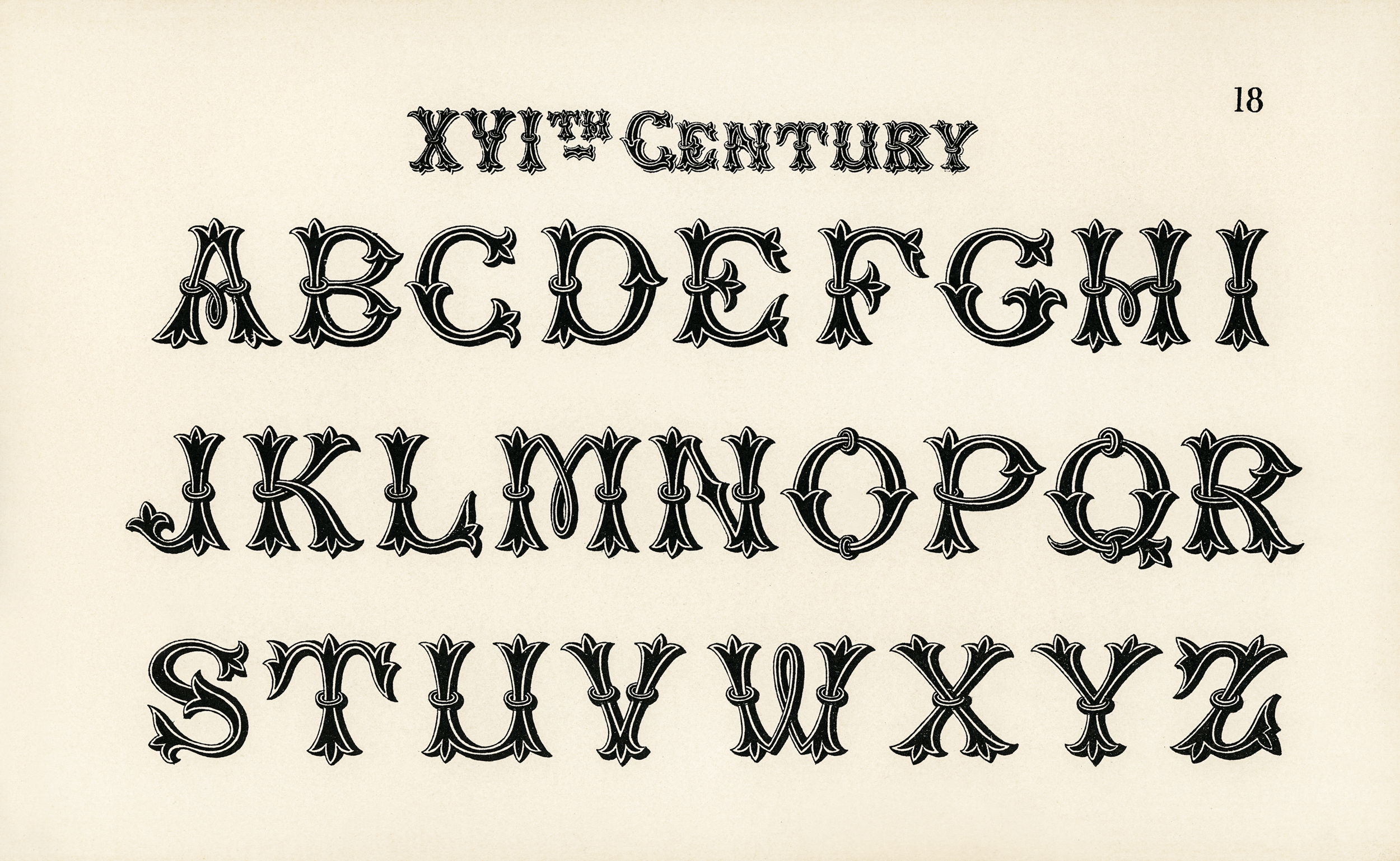
Мы много говорим об универсальных «рабочих лошадках». Такие шрифты популярны, их характер чаще нейтрален, а кассовый состав — обширен. Один такой шрифт, например, TT Norms® Pro, может использоваться в тысяче проектов с разной тематикой и выглядеть уникально в каждом.
Универсальные шрифты очень востребованы. Но чем расставлять акценты? Можно использовать и «рабочие лошадки», но, когда нужно передать сильную эмоцию, лучше поискать вариант с более выразительным характером.
Сегодня речь пойдёт о них: изящных и дерзких, дружелюбных и брутальных, динамичных и устойчивых.
Это — шрифты для акциденции. Они бывают разными по характеру и уровню выразительности, но всегда привлекают внимание читателя при правильном использовании.
Какими бывают шрифты для акциденции
Декоративных шрифтов не бывает много. Коллекция таких шрифтов у опытного дизайнера может превышать 400 гарнитур, и это далеко не предел. Потребность активнее пополнять коллекцию акцидентных шрифтов связана с тем, что подбирать их нужно более тщательно.
Декоративный шрифт должен подходить проекту безупречно, ведь именно в заголовках, логотипе и других крупных надписях заложены эмоциональные посылы, которые считывает аудитория.
Это шрифты, которыми привлекают внимание. Даже начинающий дизайнер понимает, что большой массив текста и заголовок не стоит набирать одним шрифтом и кеглем. В тексте важны акценты. От того, как их расставит дизайнер, зависит заинтересованность читателя.
Задача шрифта для набора текста — не отвлекать внимание от чтения, а акцидентного шрифта — привлекать.![]()
Хоть шрифты для акциденции — широкая группа, объединяющая множество стилей и видов, вы легко отличите их от других. Такие шрифты хочется разглядывать и изучать каждый штрих буквы, особенно когда текст набран в крупном размере.
В этой статье мы поговорим о трёх категориях шрифтов: об акцидентных, дисплейных и декорированных.
12. Guest Lunch
Что нам нравится в Guest Lunch, так это не только его универсальность, но и его классический дизайн, который отлично подойдет для любого проекта или рекламной акции. С включенными глифами, альтернативами и пунктуацией, что может не понравиться?
13. Второе царствование
Этот волшебный шрифт с экстремально разнообразными границами и ромбами переносит нас в славные миры золотых времен эпических саг.